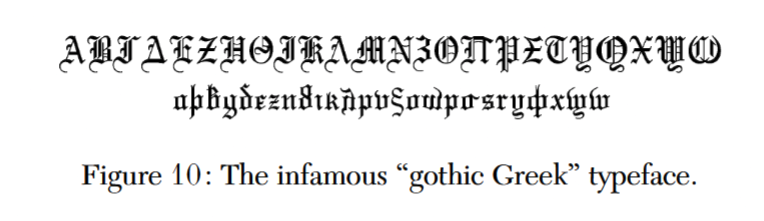
Griechisches Alphabet (Glyphen) in Fraktura
Hallo zusammen, ich suche eine Schrift, die das griechische Alphabet in einer Fraktura Typo darstellen kann. Hat irgend wer eine Idee, ob es diese Typo gibt und falls ja, wo ich sie finde? Ich bin dankbar um jede Fährte und jeden Hinweis. Liebe Grüsse, Sybill
Ja, es gibt sie.
Beispielsweise: https://www.myfonts.com/de/collections/aj-quadrata-font-adam-jagosz?tab=familyPackages
Es gibt noch mehr, aber mir ist Griechisch in gebrochenen Zügen derart fremd, dass ich mir das nicht gemerkt habe. Wenn mir im Laufe des Tages noch etwas einfällt, poste ich es hier.
Ich find grad die Festplatte mit dem PDF nicht, aber ich glaube, dass Juan José Marcos eine Broken Greek Letter abgebildet hatte in seinem Buch zur Geschichte der griechischen Typographie: https://typofonts.com/greektypography.html
Ich kann mich nicht erinnern, dass irgendwer solche Schriften mal schön gefunden hat.
Hallo Sybill, deine Suche erinnert mich an meinen allererste Anfrage hier im Forum. (Das Ergebnis für gebrochene Griechisch war damals ergebnislos. Heute haben wir Phoibos als Griechisch-Experten. :gimmifive:)
Und nur ganz fahrlässig grob, denn ich bin kein echter Experte in Sachen Schriftkunst und der Geschichte selbiger, finde ich Gebrochene Schriften dem Charakter des Griechischen fremd.
Das gedruckte Griechisch hatte stets eine enge Beziehung zum handschriftlichen Notierung. Die Zeit der Gotik kannte kaum Griechisches, die ersten griechischen Lettern basierten auf der Handschrift von Menschen, die nach dem Fall Konstantinopels gen Westen flohen und nicht nur Griechisch ins Europa brachten, sondern auch die Fundamente des Humanismus legten – und in Italien in gegenseitiger Befruchtung griechische Lettern und die Antiqua »erfanden«: berühmte Kooperationen von Druckern wie Aldus Manutius mit Humanisten wie Laskaris prägten nicht nur längst vergessene Werke der Antike, sondern auch die europäische Geschichte.
Hallo Phoibos, danke für die Links, den Screenshot und deinen historischen Hinweis. Ich bin bildende Künstlerin und dass ich die griechischen Glyphen in Fraktura abbilden möchte, hat einen konzeptuellen Hintergrund für die Arbeit und weniger einen Ästhetischen oder historischen. In der Kunst werden oft "Dinge" neu kombiniert, die so noch nie zusammengefunden haben 🙂
Hier noch ein paar Gedanken dazu: